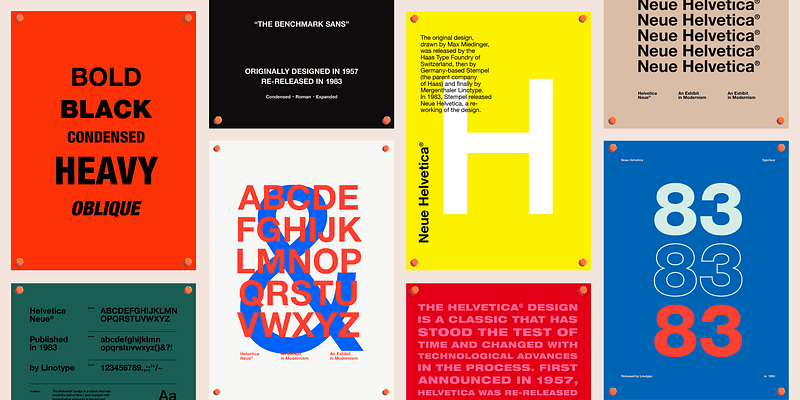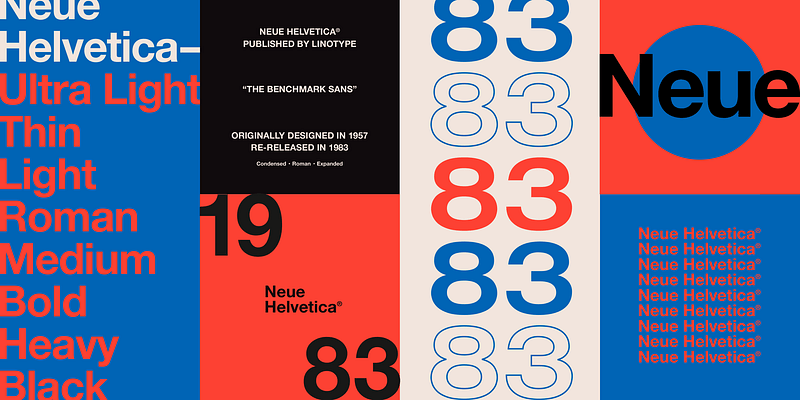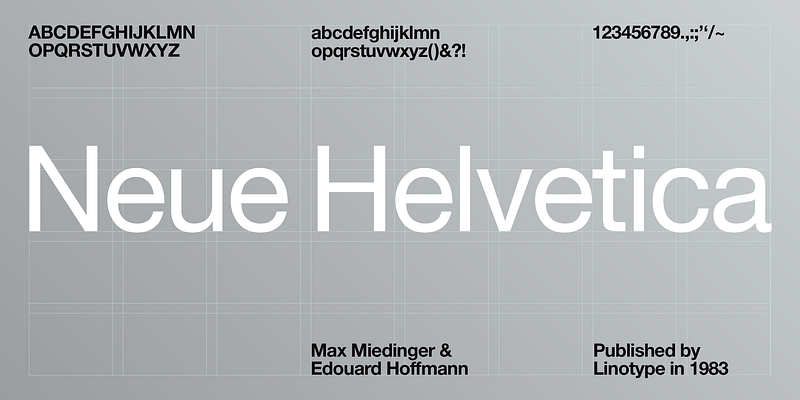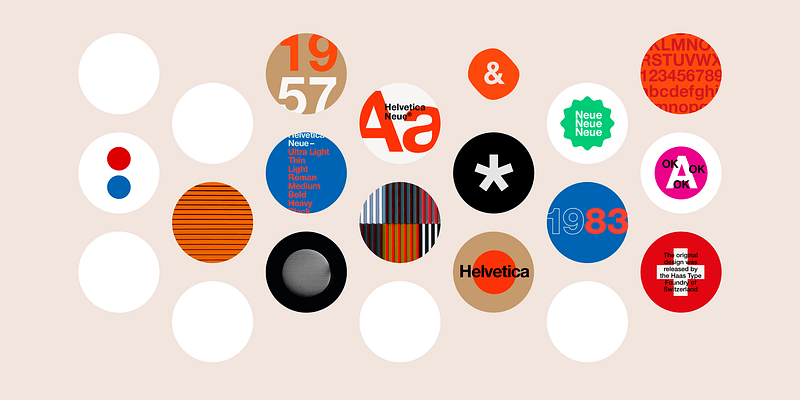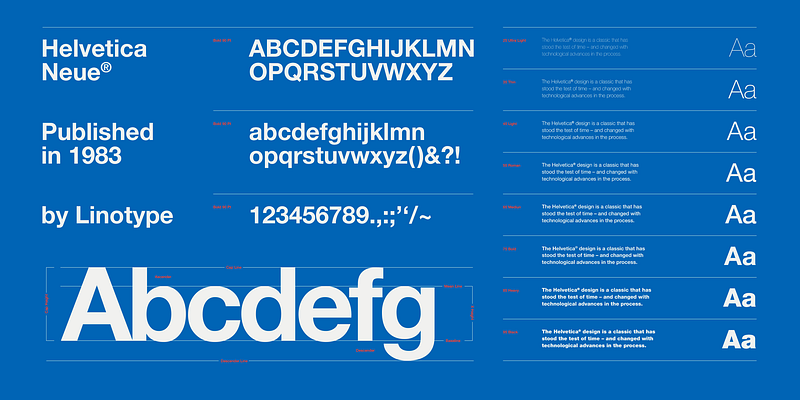
Neue Helvetica®는 미적 및 기술적 개선을 결합하여 탁월한 디자인 비율, 향상된 가독성, 원래의 Helvetica 글꼴을 넘어 확장된 사용 범위를 제공합니다.
Neue Helvetica World 글꼴을 사용하면 아랍어, 아르메니아어, 키릴 문자, 조지아어, 그리스어, 히브리어, 태국어 및 베트남어 외에도 범유럽 언어를 설정할 수 있습니다. 키릴 문자 글꼴은 불가리아어, 마케도니아어, 세르비아어 및 우크라이나어 문자를 포함하여 유니코드 블록을 완벽하게 지원합니다.
다른 Monotype 글로벌 글꼴을 Neue Helvetica World와 함께 사용하면 보다 포괄적인 글로벌 타이포그래피 솔루션을 만들 수 있습니다.
몇 가지 예는 다음과 같습니다.
데바나가리: Saral Devanagari
일본어: Tazugane Gothic 또는 Yu Gothic
한국어: YD Gothic 100 또는 YD Gothic 700
중국어 간체: M Ying Hei PRC 또는 M Hei PRC
중국어 번체: M Ying HK 또는 M Hei HK